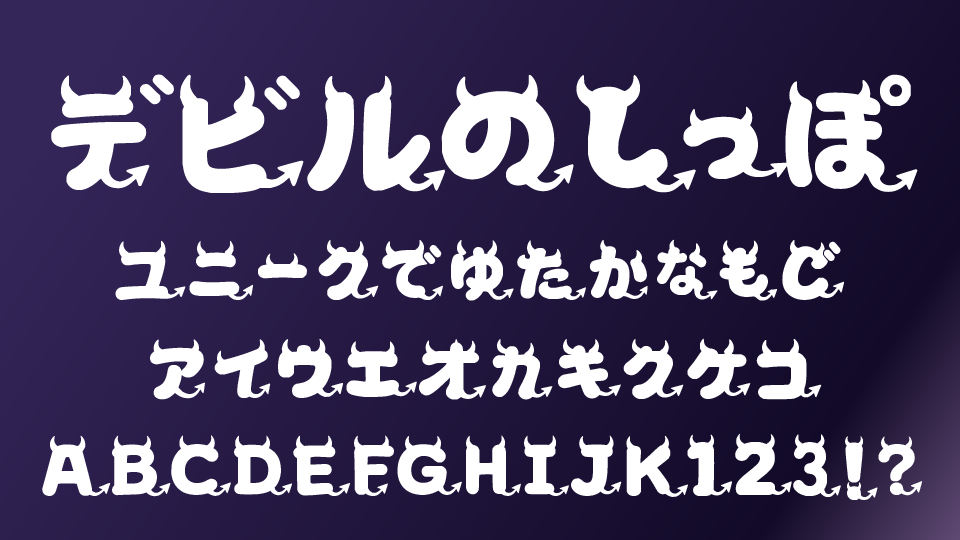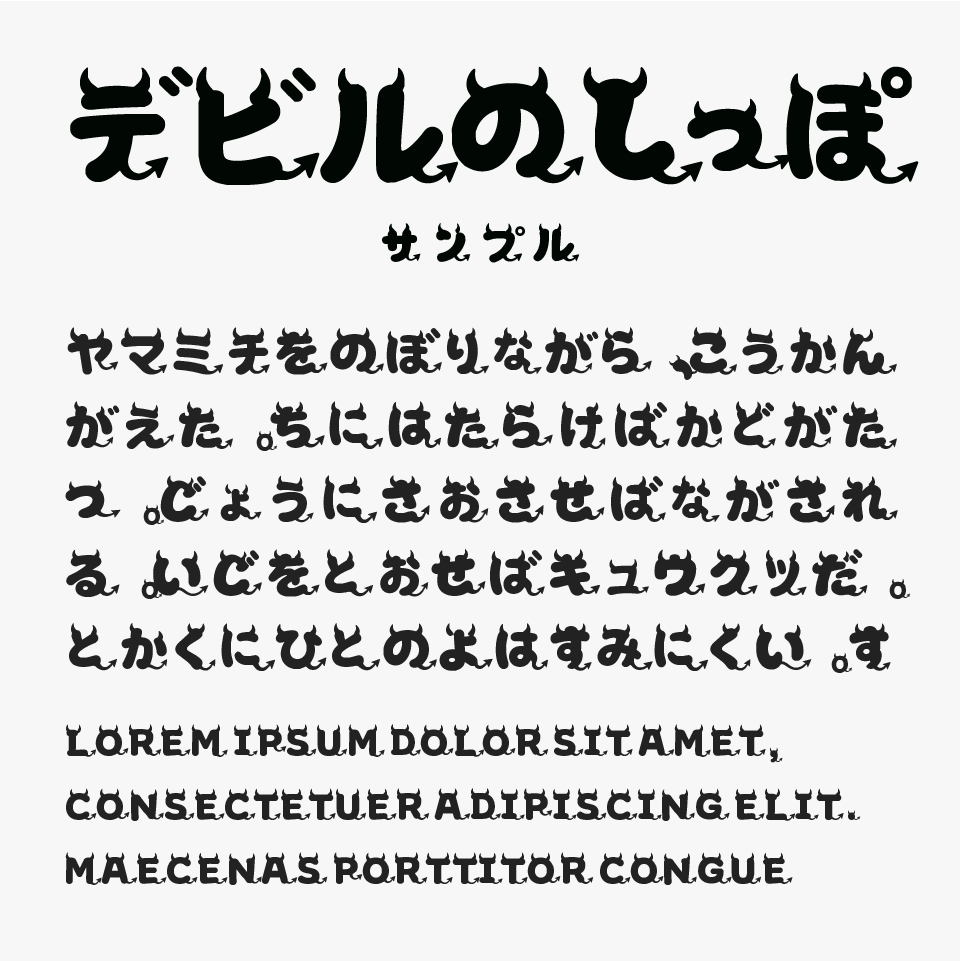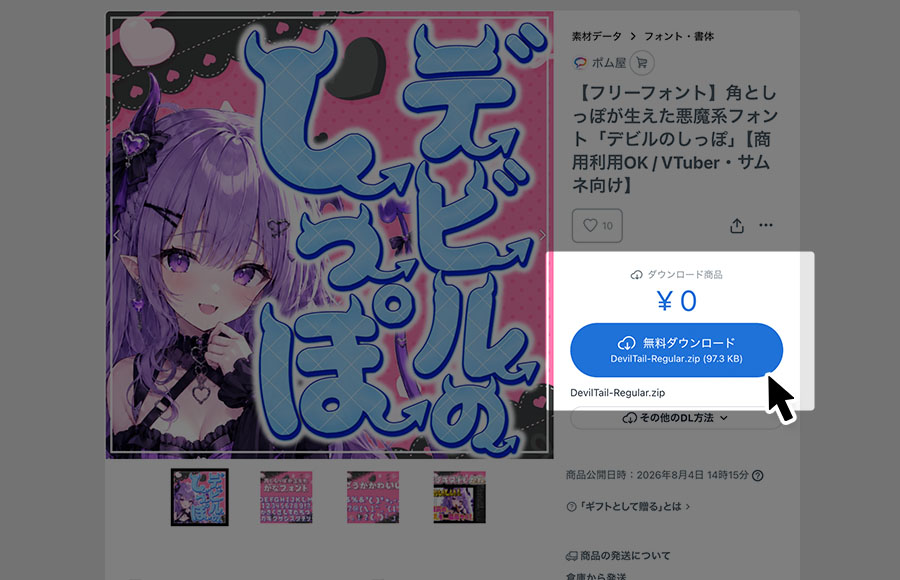
デビルのしっぽ
デビルのしっぽフォントは、文字の端々に悪魔のツノやしっぽを思わせる鋭い装飾を取り入れた、可愛さと遊び心あふれるデザインフォントです。
シルエットにはダークファンタジーの雰囲気が漂い、可愛らしさと少し怪しげな空気感を絶妙なバランスで、THEホラーというフォントではなく、コミカルな悪魔モチーフとしても使いやすいフォントです。
ハロウィンイベントやゲーム、VTuber、YouTubeサムネイル、グッズデザインなど、インパクトのあるデザインにぴったりなフォントです。キャラクター性をしっかり演出できるため、ダークポップやファンタジー作品とも相性良く活躍してくれます。
収録文字は、ひらがな・カタカナ・アルファベット・数字・記号が収録されています。